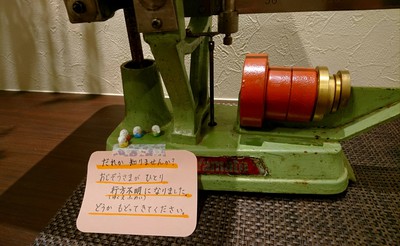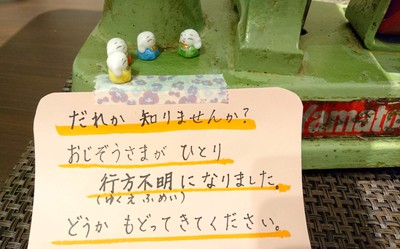
アレやってよ~って言われてたし♪
時々、
「ブログ見てます!」
ってお声を頂くようになってきました♪
そんな時、よく言われるのが
『美文字への近道』
文字の書き順のやつ、面白いですよね~って。
そういえば
最近、あげてなあったわ~(汗)
・・・というわけで
先日の
『オトナの美文字ワークショップ』から
皆さんと共有した
間違えやすい漢字をご紹介♪
『祝』
のし袋やのし紙に覚えておくと便利かも♡
↑1画目 テン!丁寧に書いて見て~
↑2画目 右上がりに~
↑3画目 ここが間違えやすいね♪
1画目の真下にもってきて~
↑4画目 テンこちらも丁寧に~
↑5,6画目 2画目の右上がりと平行に~
↑7画目 右上がりのままに~
↑8画目 口の左側に置く
↑9画目 口の中心あたりからのびやかに~
いかがでした?
まだ、共有したい感じあったので
またアップしますね~♪
自分の名前くらいは上手に書きたい・・・!
たくさんの
「はじめましてさん」にも参加いただけた
『オトナの美文字ワークショップ』
~名前を書こう!~筆ペン講座
無事、終了しました~♪
毎回、参加者さまが
違うんで教室風景が
参加者さま色に染まるんですが
いずれの教室も
楽しい時間が過ごせました。
変わらないのは
基本をお伝えするって事、
何度も参加いただいてる方にも
ついつい
日頃のクセが出てしまってるのを
正しい姿勢や持ち方に引き戻せるいい時間♪
なかには
思う様に書けず悔しくって
足もしびれちゃうし~
「う~・・もう帰りたい・・・」
なんてお声が!!
「え~!そんな事言わないで~
わたしのことは嫌いになっても
文字書くことはキライにならないで~!!」
(笑)(笑)(笑)
たくさんのことを
持ちかえらなくってもいいんです!
なにか1つ覚えて帰っていただければ
それだけで美文字への変化なんです♪
彼女は「岩」の美文字を
持ちかえっていただけたようで
ホッとしました~♡
劇的な姿勢の変化が
あった方も・・・
↑力抜いてね~とアドバイス
させていただいたら姿勢が良くなりました。
↑姿勢がよくなると用紙もまっすぐに・・・
↑左手が正しい位置になると
姿勢が美しくなりました。
↑同じく左手の位置で変わりました。
また
いくつか書き順を
共有したい文字もありましたので
それはまたの機会に~♪
今夜もオトナの美文字ワークショップ♪
午前、午後の部終わり、
夜の部 控えて休憩中~
毎回思うんですが
みなさん
『オトナの美文字ワークショップ』後の
笑顔が素敵~♪
写真や文章まとまらないんで
とりあえずのご報告で失礼します。
また
後日、じっくりたっぷり
ワークショップ風景を
アップしたいと思いま~す♪
・・・しばしお待ちを~♡
本日、オトナの美文字ワークショップです!
おはようございます!!
さぁて!
本日、
『オトナの美文字ワークショップ』です
~筆ペンで 名前を書こう!~
こちらのテーマでのワークショップは
高山では2度目♪
皆さんが
なにかしら持ちかえって頂けるよう
がんばります!!
筆ペンで
ご自身の名前を美文字に書けるようお稽古できる講座です。
文字やイラストを自由に描いて